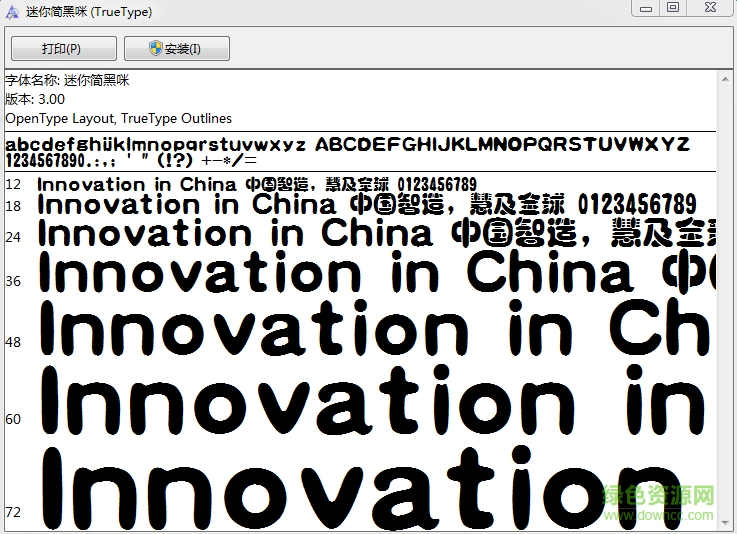
迷你簡黑咪字體可以在多個行業(yè)進(jìn)行設(shè)計使用。比如說設(shè)計平面廣告、印刷廣告等等。本字體外形規(guī)整,輸出的字體非常醒目亮眼!喜歡的用戶快來下載安裝吧。
迷你簡黑咪字體是一款粗體迷你字體,雖然是粗體,但是寫出來的字依舊美觀,應(yīng)用范圍廣,比如廣告設(shè)計、題詩題詞等,用處還挺多的,歡迎大家來綠色資源網(wǎng)下載使用。